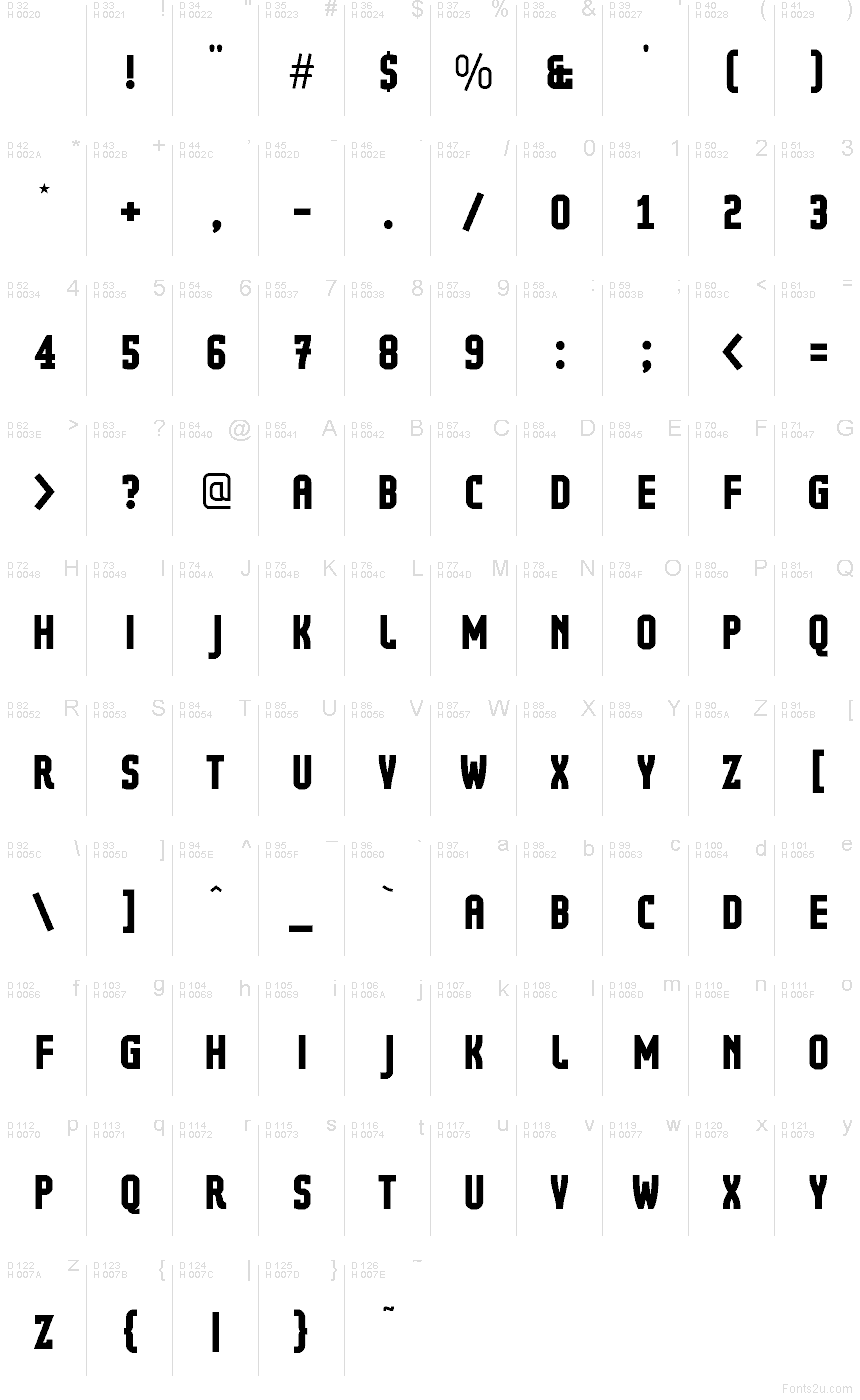
Sumpfdeutschensportschrift SdIN Bold, de Tup Wanders, é uma fonte esportiva sans serif construída com maiúsculas compactas e diretas, com um ritmo atlético e depurado. As letras parecem pressionadas em formas retangulares apertadas, com entalhes profundos e ângulos quadrados que conferem à fonte uma atitude robusta, estilo cartaz de ginásio antigo, em vez de uma estética moderna neutra.
É perfeita para títulos de cartazes, branding de equipas, flyers de eventos, gráficos de merchandising e cartões de título onde palavras curtas precisam daquele impacto comprimido e afiado. Como é uma fonte gratuita, também funciona muito bem em capas e monogramas, já que as maiúsculas se encaixam com uma presença densa, semelhante a uma faixa.
Em 2022, a divisão esportiva do que era então o Sumpfdeutsche Institut fuer Normung (SdIN) convidou um grande grupo de treinadores esportivos internacionais, atletas, designers de moda, árbitros e tipógrafos para um seminário em Neuschanz (Gr) para determinar se seria possível estabelecer um padrão comum para a tipografia em equipamentos esportivos.
Durante anos, os árbitros reclamaram da má legibilidade dos tipos utilizados nas camisas dos jogadores em diversos esportes. Foi selecionada uma força-tarefa de profissionais importantes e, após três anos de análise, o grupo descobriu que poucos tipógrafos ou designers de fontes estavam dispostos a lançar um design sem a possibilidade de monetizá-lo.
O Instituto pediu ao designer de fontes local Tup Wanders, conhecido por disponibilizar todas as suas fontes de forma gratuita e em código aberto, que desenvolvesse um design. Após pesquisar o uso da tipografia esportiva, assistir a centenas de horas de filmagens de esportes e experimentar alguns esportes ele mesmo, Wanders concluiu uma definição global gratuita e de código aberto da Sportveranstaltungenindustrie-norm em menos de três dias.
Todos os caracteres especiais e diacríticos usados por idiomas de escrita latina foram incluídos. A definição é totalmente gratuita e livre de direitos para uso por atletas, fãs de esportes e organizações até 2030, quando um seminário de acompanhamento em Neuschanz avaliará melhorias.